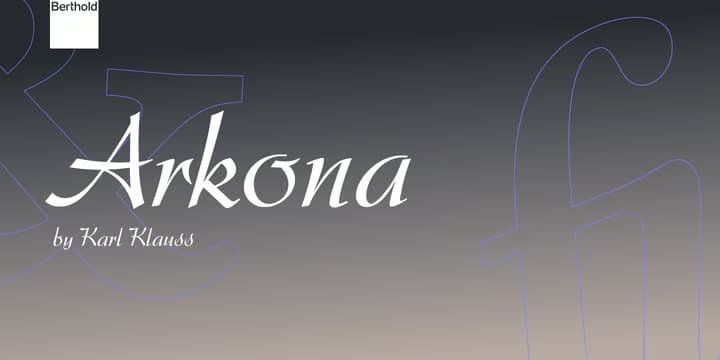
Arkona
古いカリグラフィー風味のあるタイプスクリプト。コネクションのない活字風のタイプで、ブロードペンで書いたようなストロークのエレガントで端正な書体である。ざっとグリフをチェックしたが、多分筆者はこれを書くのは難しくない。それぐらい自然なストロークだけで構成されている。雰囲気はキリッとしててやや男性的だろうか。やはり大きく使うものではなく、小さなカードなどに似合うだろう。2ウェイト。